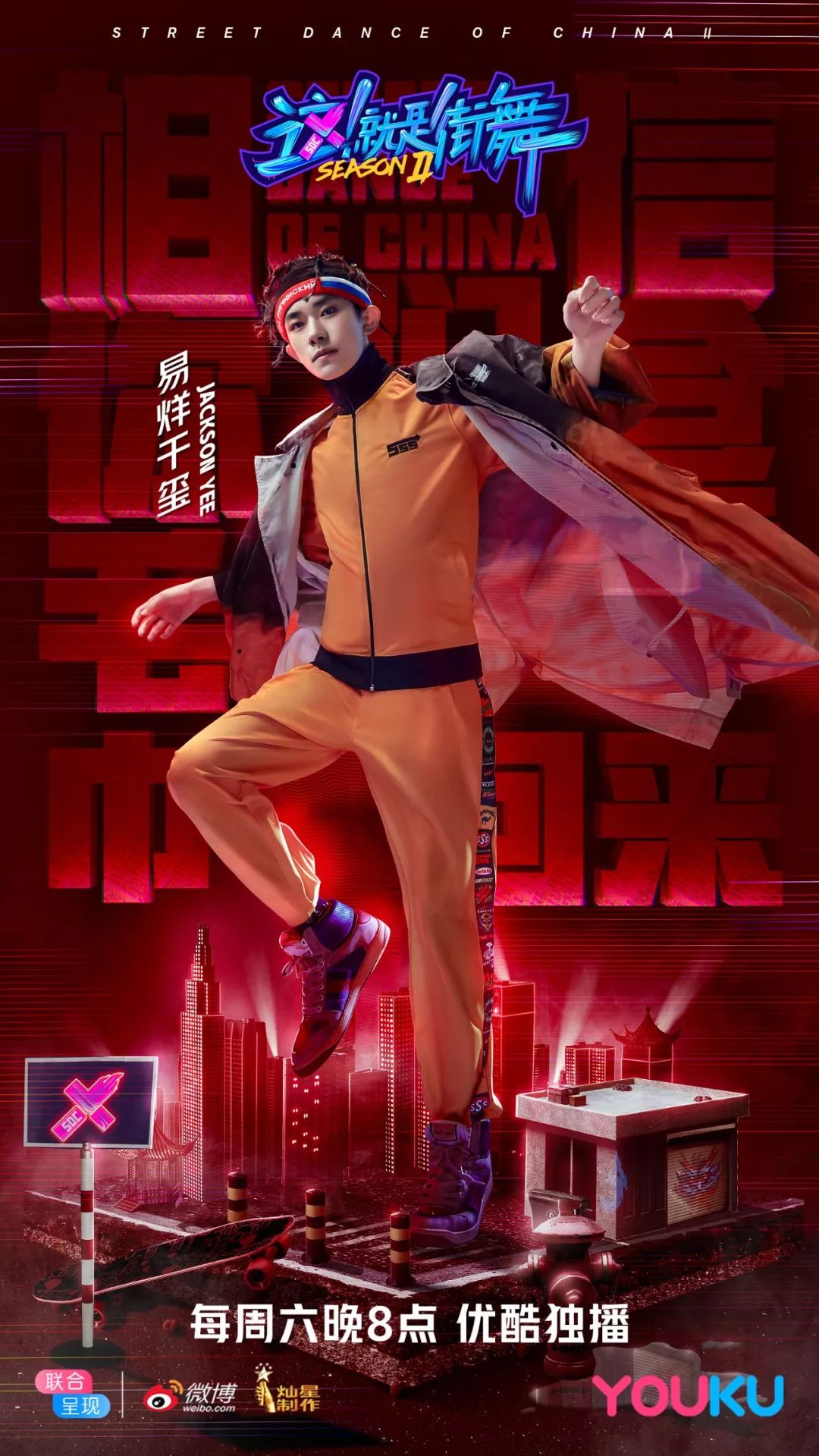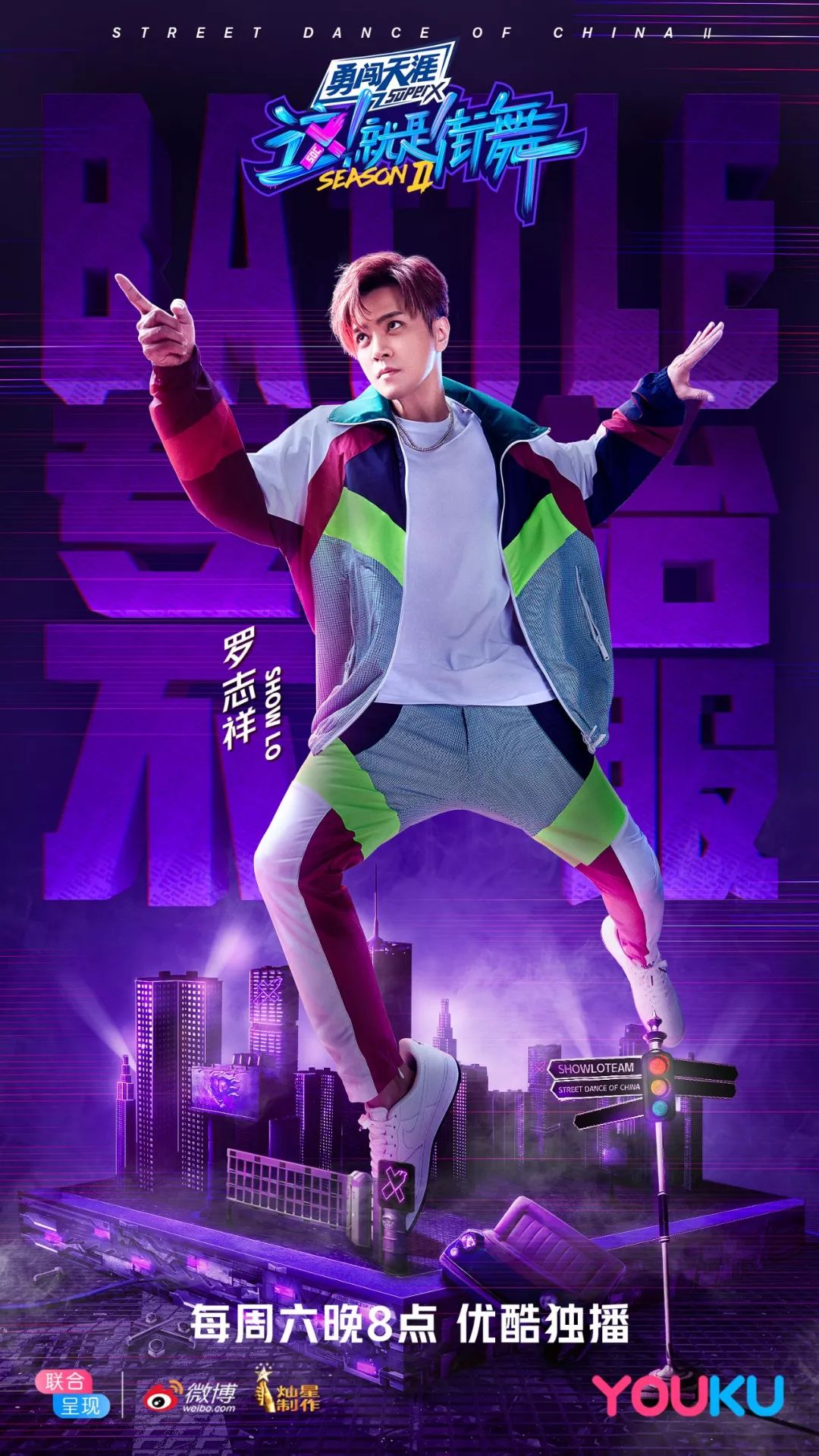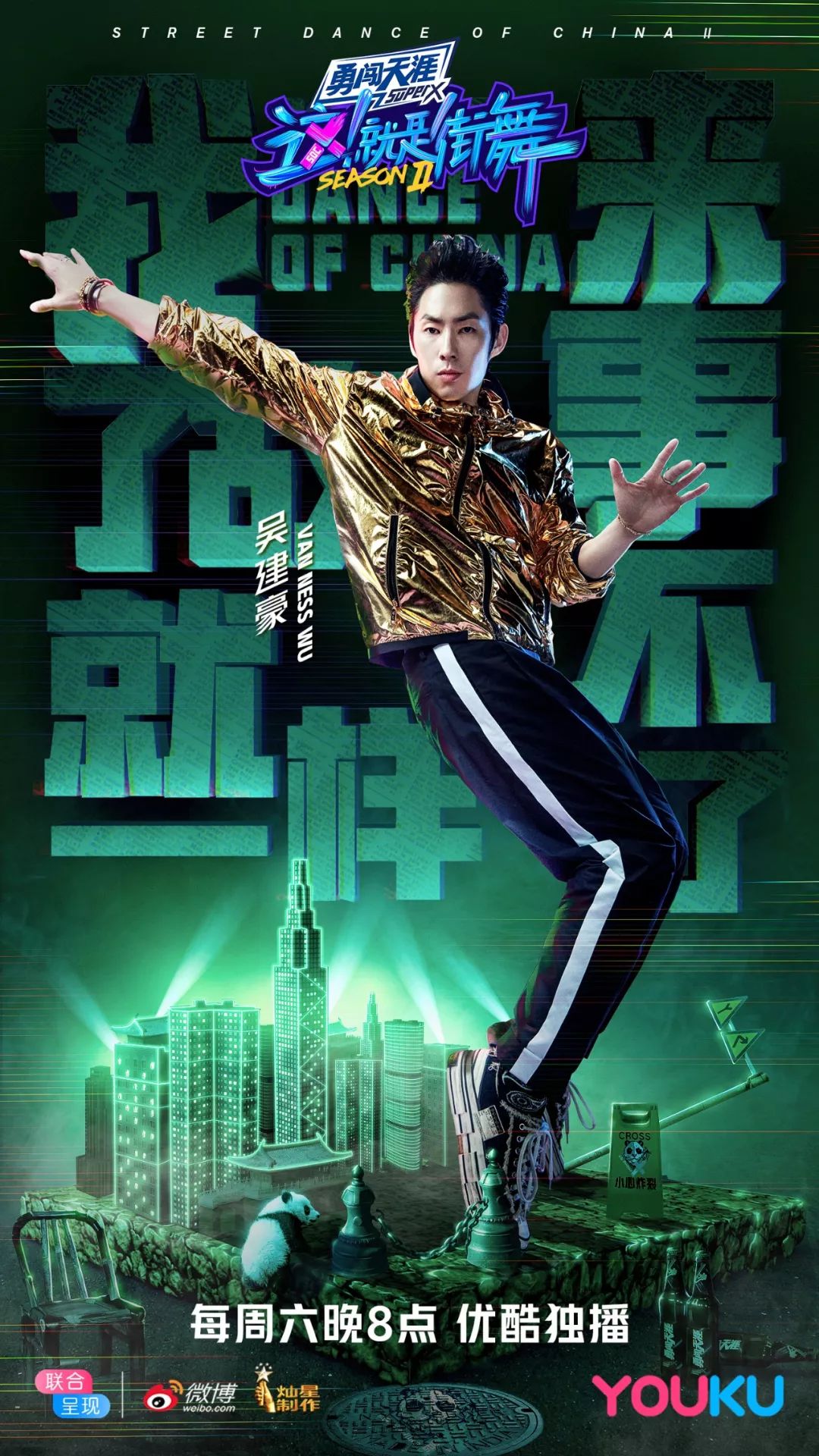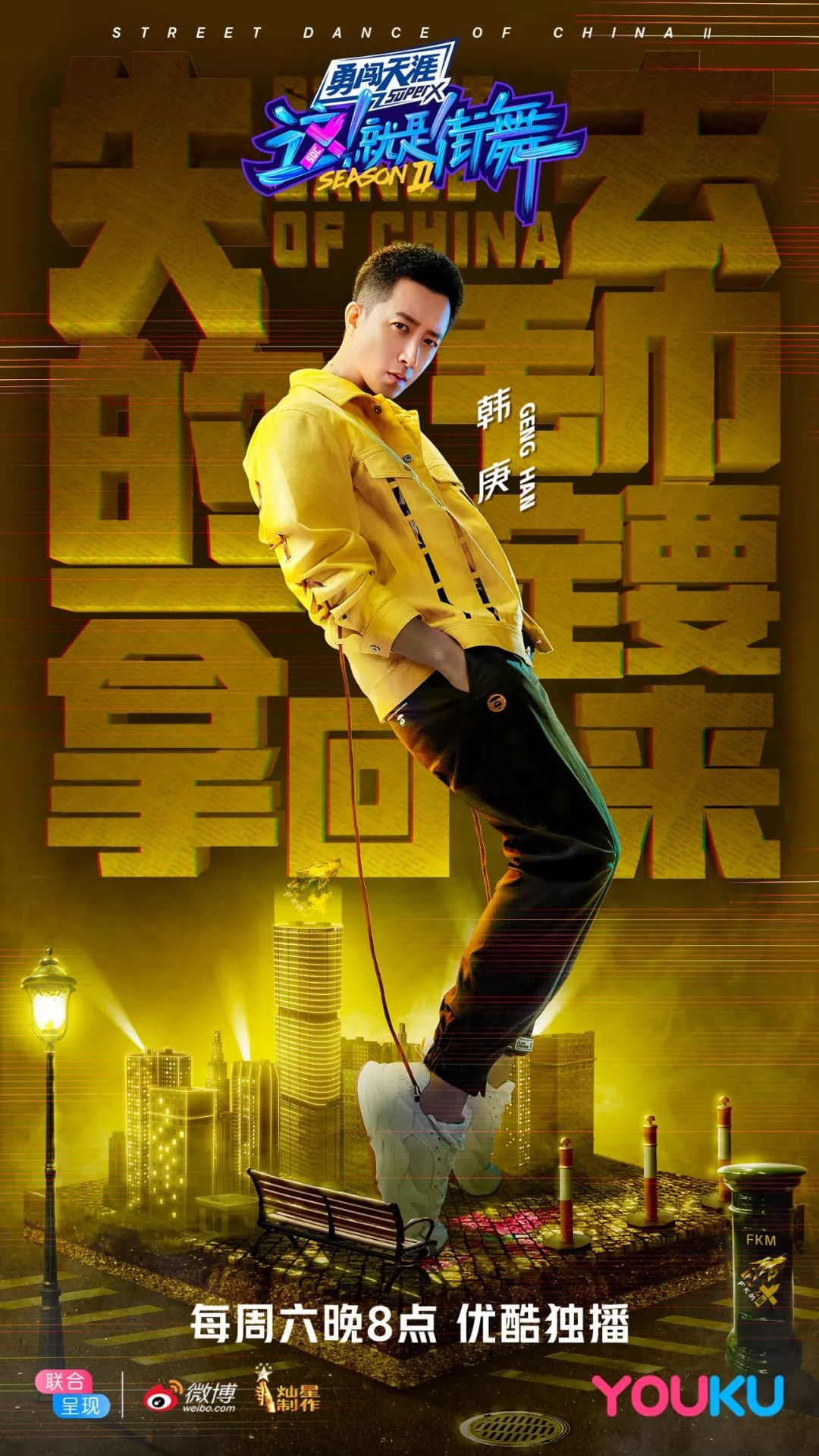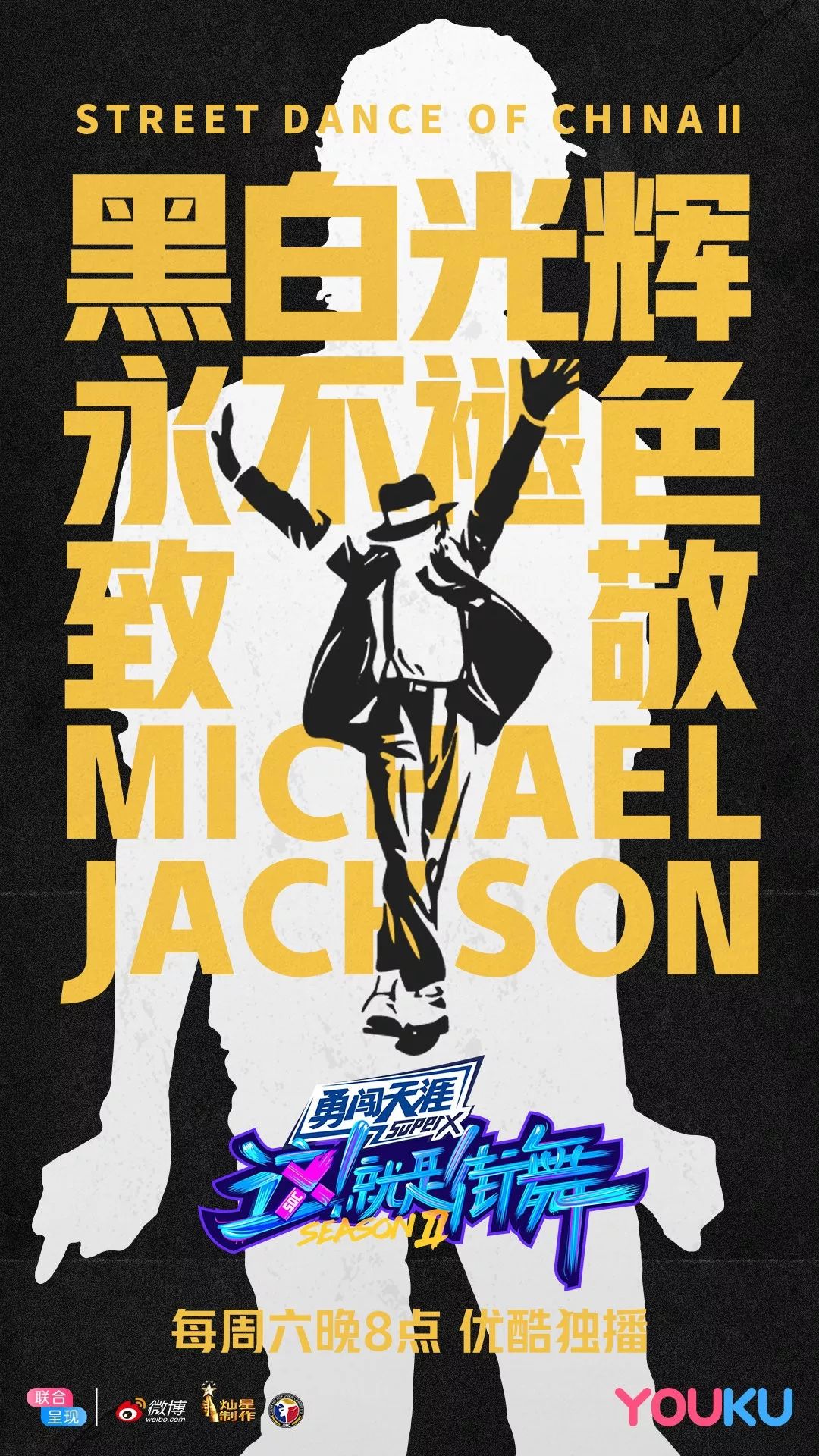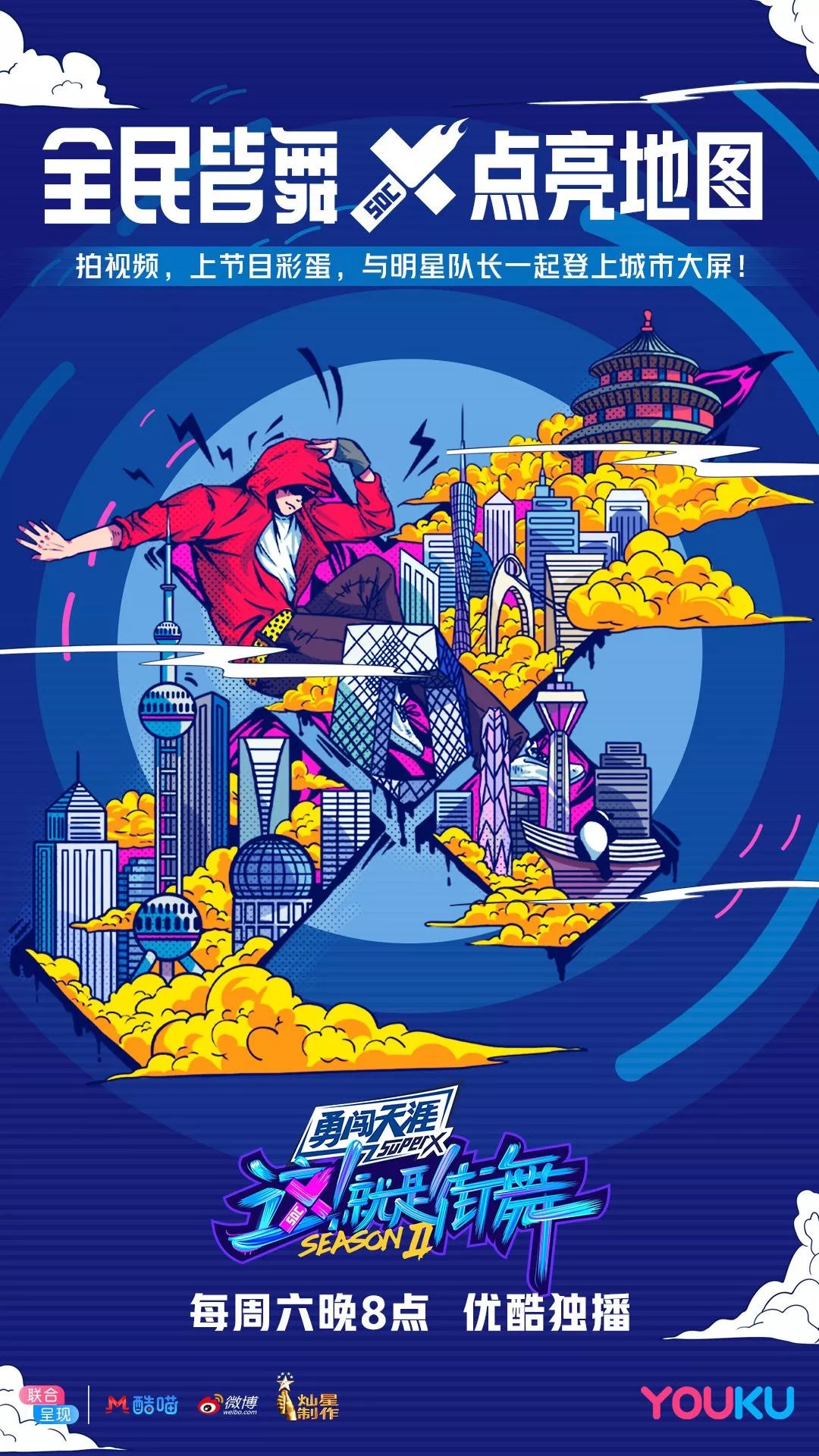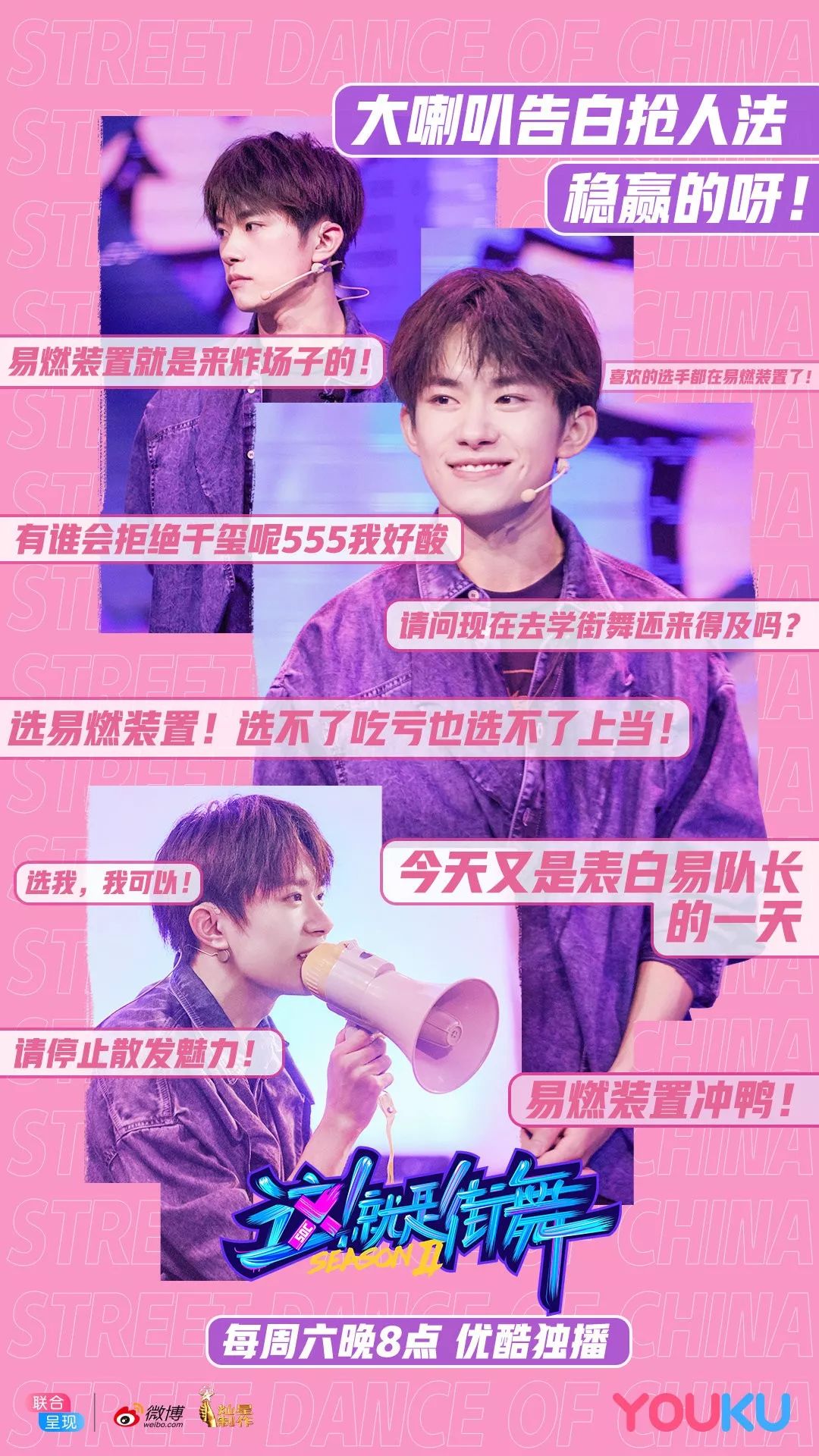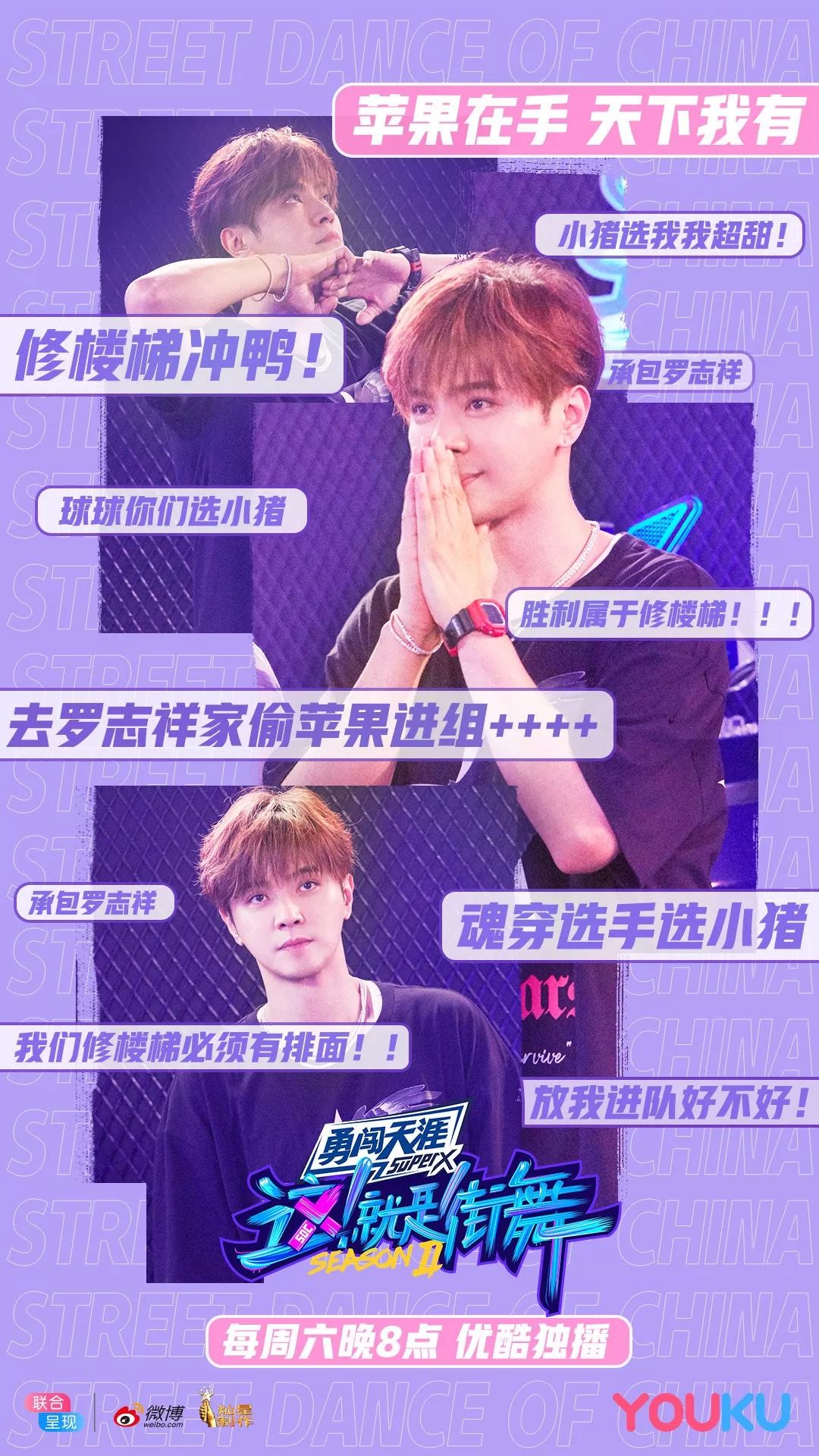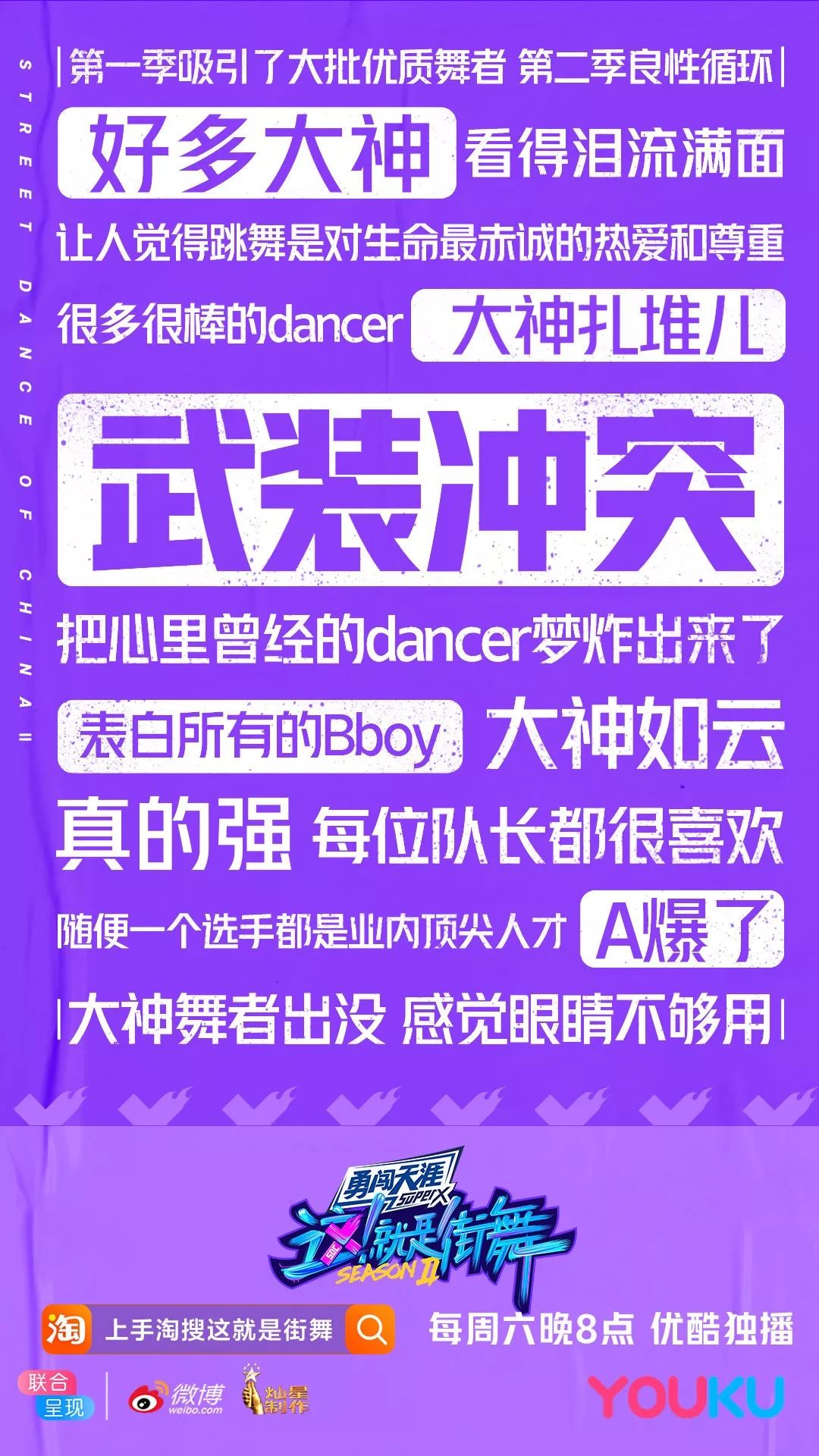
不得不说,这就是街舞的设计,简直好看到爆炸!
其实柚子之前一直没关注过这档综艺,据说是看着热血沸腾!
晚上睡不着觉那种……
不过这都不是打动我的原因,而是看到这个字效,哇哦~
上一季还是这样的,感觉这季更潮、更精致了,还加了两道“小毛巾”。
想实现也不难,就是在字形的基础上,用画笔和涂抹工具刷出来,有耐心一点就好。
不过我今天想说的是《这就是街舞》的其他设计,比如场景的用色,有一种赛博朋克之美。
社交媒体上运用了抖音的故障特效,既符合街舞的动感,也满足当下年轻人的审美。
▲汉仪雅酷黑
▲汉仪天宇风行体
在构图上,运用几何色块和笔触元素,让人物聚焦,画面有层次感。
▲汉仪迪升英雄体
文字铺底的海报设计,也做得特别立体,爱死吴建豪这张了~
▲汉仪力量黑
就连广告植入的插画,也跟毛巾完美融合,甲方爸爸要感动得哭~
▲汉仪雅酷黑
Michael Jackson那期特别经典,海报也是特别有感觉~
▲汉仪雅酷黑
你也许发现了,在街舞的许多设计中,都有汉仪雅酷黑的身影……
你确定不是用来展示字体的吗?哈哈哈~
当然也有更年轻、更炸裂的新字体!
▲汉仪迪升英雄体
▲汉仪天宇风行体
还需要偶尔卖个萌的可爱字体~
▲汉仪铸字童年体
so留个小作业,下面这张图,共有哪三种字体?可以去字由官网找哦~